타이포그래피 실험정신_오데드 에저
오데드 에저는 이스라엘의 젊은 디자이너다. 스스로를 타이포그래피 실험가라고 소개할 만큼 그의 디자인은 상당히 기이하고 파격적이다. 전혀 어울릴 것 같지않은 타이포그래피와 바이오테크놀로지를 조합하는가 하면, 마치 행위 예술과도 같이 자신의 육체와 타이포그래피의 연결하기도 하는 등. 에저의 디자인 실험은 지금까지의 타이포그래피 디자인과는 전혀 다른 개념을 보여준다. 그가 이런 디자인 실험을 하며 던지는 메시지는 단순하다. 우선은 재미있다는 것이고, 그리고 재미를 통해 타이포그래피의 새로운 가능성을 찾을 수 있다는 것이다. 뉴욕타임즈는 오데드 에저를 이렇게 표현하기도 했다. “Fascinating!”
국내 독자들에게 간단한 자기 소개 부탁 드립니다.
저는 예루살렘에 있는 베자렐 예술 디자인 학교(Bezalel Academy of Art & Design)를 졸업했고, 2000년부터 제 이름을 건 ‘Oded Ezer Typography’라는 독립 스튜디오를 설립하여 운영 중 입니다. 히브리어와 라틴 타입페이스 디자인, 타이포그래피, 브랜드 아이덴티티 디자인을 주로 하고 있습니다. 또한 ‘the Holon Institute of Technology’ 에서 비쥬얼 커뮤니케이션 강의를 맡고 있고, 전 세계적으로 여러 아카테미와 컨퍼런스에서 타이포그래피 강연 활동을 지속하고 있습니다. 제가 추구하는 것은 타이포그래피의 미래 가능성을 엿볼 수 있는 실험적 디자인 입니다.
작품들 중에서 ‘바이오타이포그래피’라는 것이 유독 눈에 띄는데, 바이오타이포그래피가 무엇입니까?
바이오타이포그래피는 미래의 타이포그래피에는 어떤 일이 펼쳐질까를 상상해보며 실험해 본 것입니다. 50년 후 타이포그래퍼들은 과연 어떤 작업을 하고 있을까요? 혹시 지금까지는 생각지 못했던 전혀 다른 방향으로 진화되지는 않을까요? 제가 떠올린 것은 타이포그래피와 과학기술의 접목이었습니다. 지금 세상의 많은 것들이 과학기술과 만나 새로운 발전을 거듭하고 있습니다. 타이포그래피도 그럴 수 있다고 생각합니다. 상상만 했던 것들을 과학기술을 통해 현실화 할 수 있는 것이죠. 지금의 타이포그래피도 IT기술과 같은 과학기술에 의해 발전해 온 것도 사실입니다. 그리고 앞으로는 또 다른 기술과도 충돌할 것입니다. 저는 이와 같은 타이포그래피의 미래의 모든 가능성에 대해 탐구하려고 노력합니다. 바이오타이포그래피는 그런 저의 실험 중 하나입니다. 타이포그래피와 바이오기술의 충돌이죠. 그런 의미에서 타이포그래피적으로 변형된 다양한 유기체들을 창조해보는 것입니다.
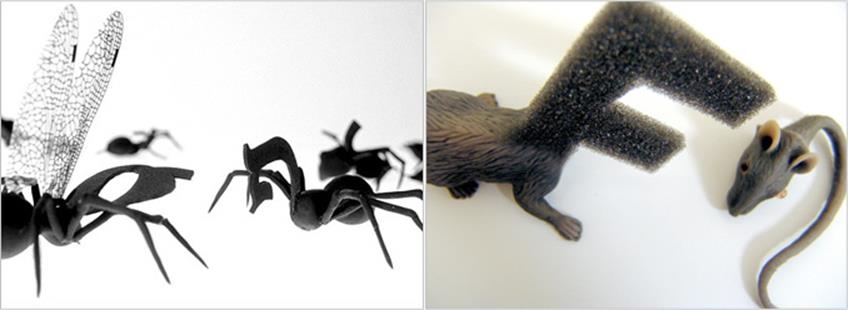
▲ Biotypography creatures. 서로 다른 문자를 가진 개체들이 모여 하나의 단어를 만들어 우리와 소통한다. 이것이 에저가 상상하는 바이오타이포그래피다.
‘Typosperma’프로젝트도 바이오타이포그래피 실험 중 나온 것인가요?
네. ‘Typosperma’는 바이오타이포그래피 실험 중 하나입니다. 이 프로젝트는 유전적으로 전혀 관계가 없는 사람과 문자가 혼합된 새로운 존재를 탄생시키는 것입니다. 타이포 정자들은 그 새로운 창조물의 DNA에 타이포그래피적 정보들을 심게 될 것입니다.
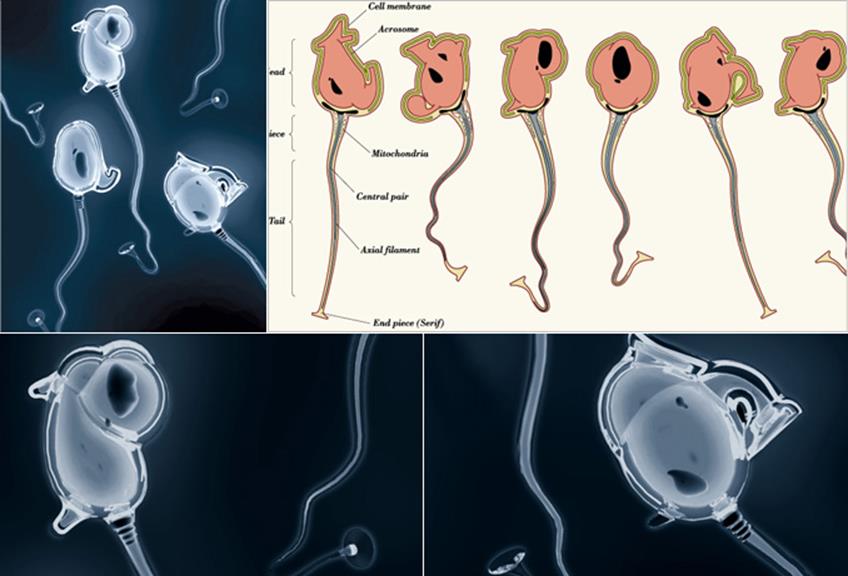
▲ Typosperma, 2006. 이 프로젝트는 지난 2008년 MoMA에서 열렸던, ‘Design and the Elastic Mind’전에 소개되어 많은 이들의 관심을 받기도 했다.
당신의 포트폴리오 중 스스로 문자를 몸에 붙인 것을 볼 수 있었는데, 이는 어떤 의미를 가지고 있나요?
‘Typoplastic Surgeries’입니다. 제 얼굴과 문자를 연결하여 진화의 한 종류를 보여주려는 것이죠. 그래픽 작업으로 진행된 이 프로젝트는 타이포그래피적 관점에서의 신체의 변형을 표현했습니다. 타이포그래피와 저는 한 치도 뗄 수 없는 관계이기도 하고, 항상 타이포그래피적 의미로 생각하고자 하는 뜻도 담겨있죠.
◀ Typosperma, 2006
위에서 보았듯 주로 실험적인 작품들이 눈에 띄는데 특별한 이유가 있나요?
첫 번째 이유는 재미입니다. 마치 어린아이들이 재미를 위해 진지하게 게임에 집중하듯, 저 역시 재미있는 무언가를 만들어 내기 위해 타이포그래피 디자인 실험을 계속 합니다. 종종 기존의 없던 새로운 것이나 기대하지 않았던 것들이 작업 속에서 보여질 때 스스로 놀라기도 합니다. 두 번째 이유이자 진짜 이유는 지속적인 실험을 통해 타이포그래피를 다루기 위한 신선한 아이디어를 얻기 위해서 입니다.
▲ Face Type, 2010. 최근 선보인 그의 또 하나의 재미있는 실험. 스카이프를 통해 다양한 나라의 사람들이 직접 제작한 글자들을 합쳐 만든 서체 프로젝트이다.
폰트도 제작하는 것으로 알고 있습니다. 특히 히브리어 폰트 제작과 라틴 알파벳 폰트 제작을 같이 하시는데, 어느 것을 더 중요하게 생각하시나요?
최근 20년 간 인터넷은 우리 삶 깊숙이 자리잡았고, 그 속에서 글로벌 언어인 영어 역시 자연스레 그 중요성을 더해갔습니다. 그러나 전 영어가 모든 나라의 문화를 대변하는 문자는 될 수 없다고 생각합니다. 각 나라마다 자신의 문화를 가장 잘 표현하는 것은 자신들의 언어일 수 밖에 없기 때문입니다. 그렇기에 저 역시 히브리어 폰트 제작에 더 많은 힘을 기울이고 있습니다. 물론 글로벌 시대에 놓여있으면서 라틴 알파벳도 중요합니다. 그러나 히브리어 뿐 아니라 각 문화가 가진 언어의 형태와 시스템에 대한 연구가 더욱 중요합니다. 때때로 우리는 이 사실을 깨닫지 못하고 라틴 알파벳에만 몰두하는 경향이 있습니다. 일례로 2000년에 일본에 간 적이 있는데 그때 일본 학생들의 전시를 볼 기회가 있었습니다. 대부분의 학생들이 영어를 사용하여 디자인을 하는 것을 보고 의아해서 한 학생에게 물었더니, 일본어는 재미가 없다는 답이 돌아왔습니다. 충격이었죠. 제가 보는 일본어는 너무도 아름다웠으니까요. 자신들의 언어를 가장 소중하게 다루는 것은 어쩌면 너무도 당연한 일이기도 합니다.
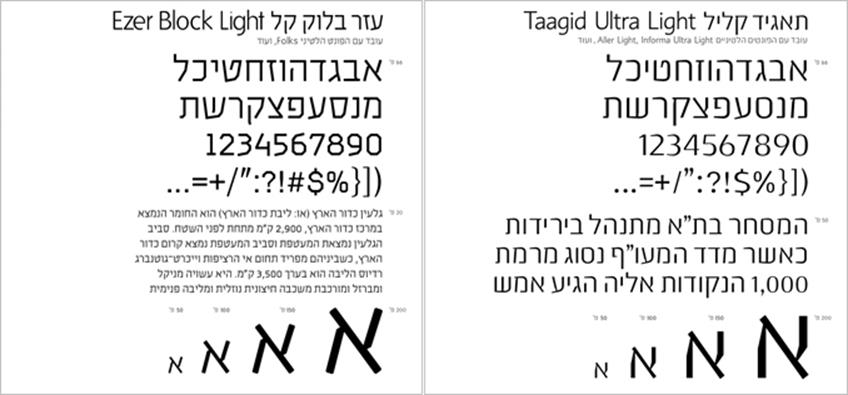
▲ Ezer Block Light
▲ Taagid Ultra Light
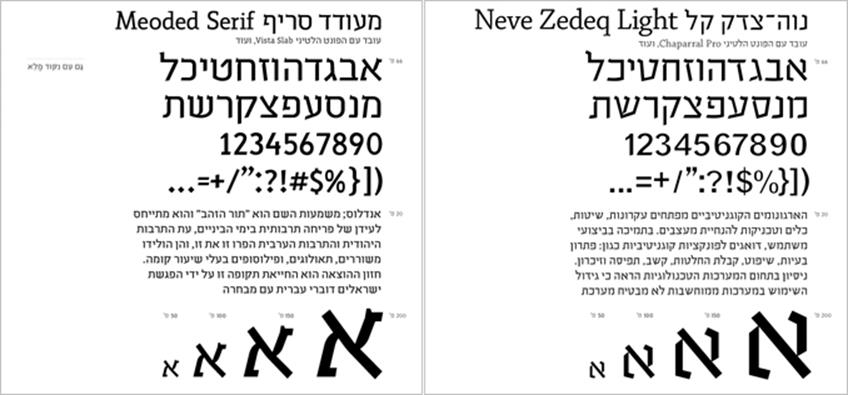
▲ Meoded Serif
▲ Neve Zedeq Light
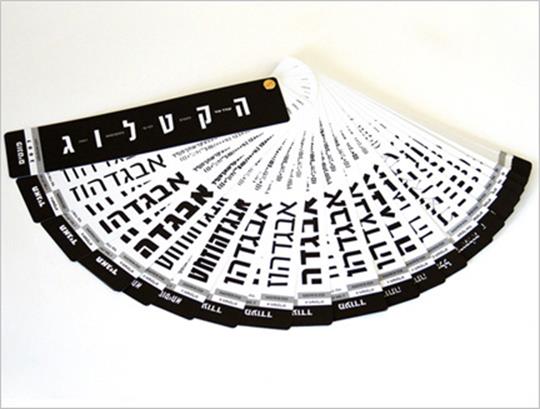
◀ Oded Ezer’s fonts catalogue, 2007
히브리어는 국내 독자들에게는 매우 생소한 언어 입니다. 히브리어 폰트를 디자인 할 때, 특별한 방식이 있나요?
히브리어 폰트를 디자인 할 때 몇 가지 방법을 가지고 진행합니다. 첫 번째는 히브리어가 쓰인 역사적 문헌 속에서 힌트를 얻는 것입니다. 오래된 책이나 캘리그래피에서 발견한 미(美)를 현대적 폰트 시스템으로 옮기는 방법입니다. 두 번째는 라틴 폰트에서 도움을 받는 것입니다. 예를 들면 헬베티카를 기본으로 비슷한 형태의 히브리어 버전을 만드는 방법입니다. 세 번째 방법은 자연이나 과학, 건축 등 조금은 거리가 있는 분야에서 흥미로운 무언가를 찾아 적용하는 것입니다.
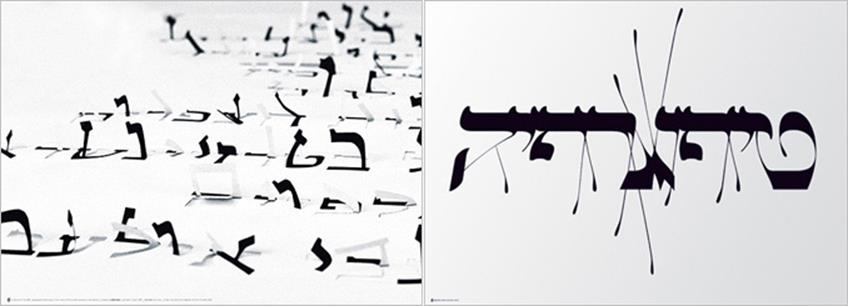
▲ The Message, 2001
▲ Tipografya poster, 2004
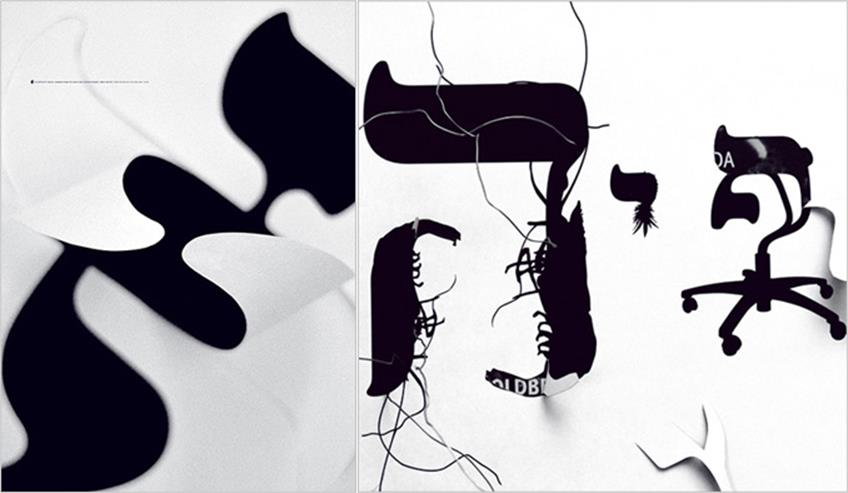
▲ Alef, 2003
▲ Tybrid, 2006
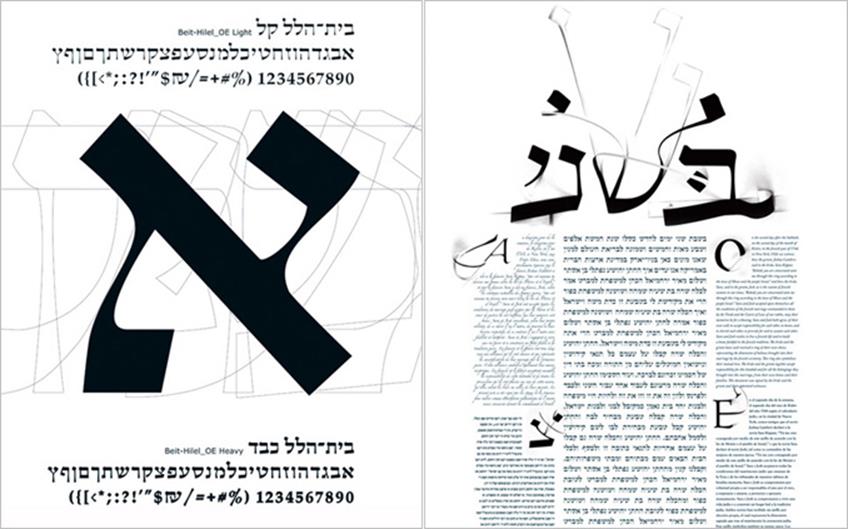
▲ Beit Hillel, 2005
▲ Ketubah, 2007
마지막으로 앞으로의 계획이 있다면?
새롭고 익사이팅한 프로젝트를 계획 중 입니다. 그것은 아마도 화학적 디자인이 될 것입니다.
▲ The Chorus of the Opera, 2001
▲ Now, 2004
▲ Unimportant & Nothing, 2004
▲ Temporary Type, 2006
▲ I Love Milton, 2008
▲ M, 2008
▲ Helvetica Live!, 2008
▲ Open, 2008